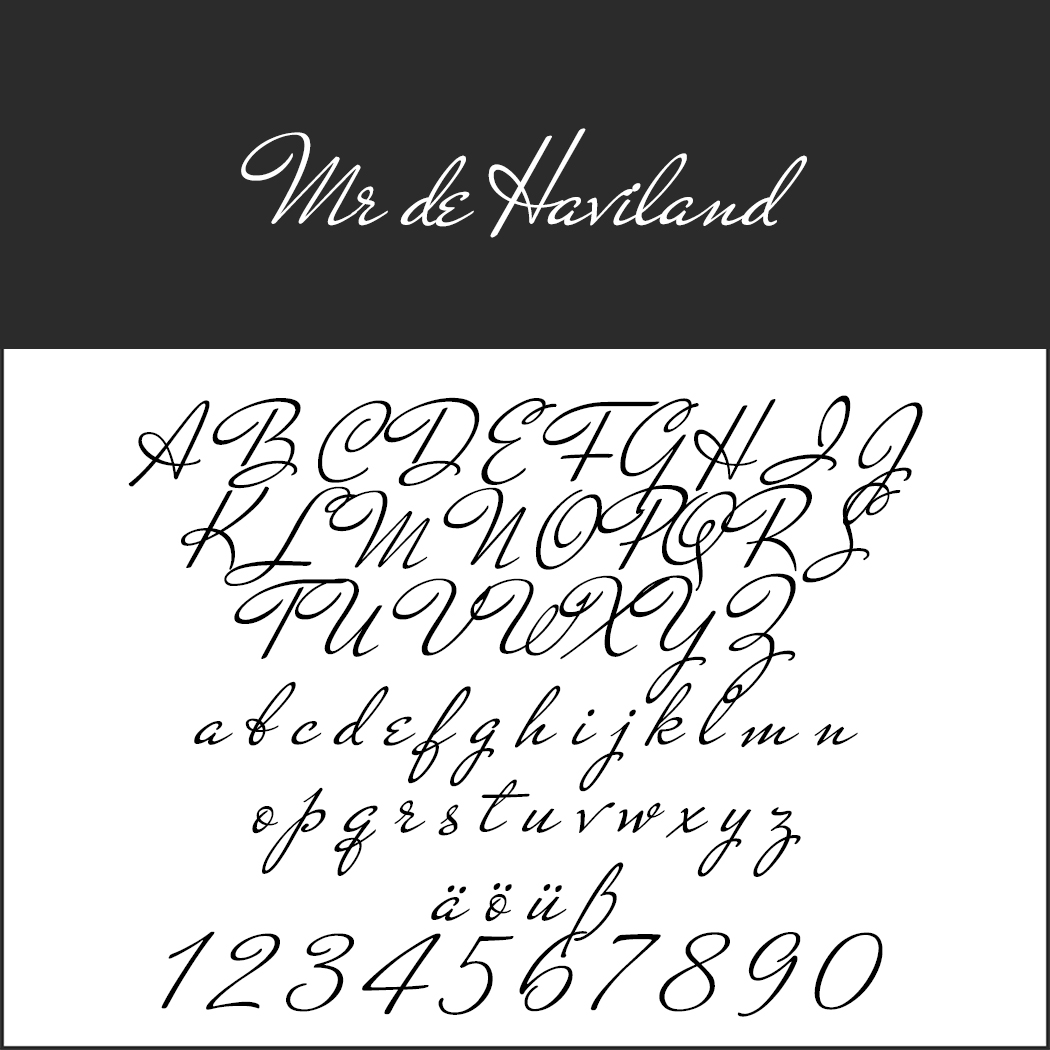
Gli affascinanti font antichi sono in grado di destare nel lettore delle sensazioni che possono essere sfruttate nell’ambito della comunicazione e del marketing. Un viaggio nel tempo attraverso il mondo dei font.
Quando un font si allontana troppo dal tipo di scrittura a cui è più abituato il lettore, salta subito all’occhio. Una capacità che rappresenta già di per sé un valore intrinseco. Tuttavia, la parte più interessante di questo processo consiste proprio nell’analizzare ciò che accade nella mente di chi legge. Infatti, disponendo di un archivio quasi illimitato di immagini, il cervello di una persona adulta è in grado di stabilire immediatamente un’associazione con il passato quando si trova di fronte ai font antichi.
La scrittura gotica rimanda subito a epoche lontane ed è pertanto ideale per pubblicizzare un mercato medievale, il corsivo dall’aspetto nostalgico ricorda più le romantiche lettere d’amore di una volta, mentre i caratteri nello stile Art déco riportano in vita i ruggenti anni ‘20. Prima di optare per un determinato font è consigliabile sottoporlo a individui diversi in modo da prevenire eventuali associazioni indesiderate, poiché l’archivio cerebrale di ogni persona è differente.
Font dallo stile antico
Gli antichi greci e romani incidevano i loro testi nella pietra o li dipingevano su pergamena, delle tecniche che al giorno d’oggi non vengono considerate affatto pratiche: esistono però dei font che riecheggiano proprio lo stile antico di quelle epoche.
Font stilizzato intitolato Art Greco, che ricorda i vecchi font. Visualizzato sia in lettere maiuscole che minuscole, ogni carattere vanta un design geometrico e angolare su uno sfondo bicolore.Art Greco
Nonostante le lettere non corrispondano esattamente agli antichi caratteri (o alla scrittura neogreca), utilizzando questo accattivante font viene subito richiamato il legame con la Grecia. Viene impiegato principalmente in campo gastronomico, tuttavia è adatto anche per altri testi che hanno a che vedere con la civiltà ellenica.
Un grafico che mostra lo stile Roman Font VII, un esempio squisito di vecchi font. Mostra l'alfabeto inglese maiuscolo completo, dalla A alla Z, e numeri romani dalla I alla X in due righe, con un design serif classico.Roman Font 7
Questo font ispirato ai caratteri romani sembra davvero scolpito nella pietra. Sono disponibili solo le lettere maiuscole, mentre per scrivere i numeri è necessario ricorrere a quelli romani.
Font medievali e rinascimentali
Con la diffusione del Cristianesimo l’influenza romana si ridusse sempre di più, un processo che si riflesse anche nella scrittura: le lettere si distanziarono dallo stile romano e diventarono più rotonde. La continua evoluzione delle grafie sfociò nella comparsa dei caratteri gotici e rinascimentali.
Immagine che mostra il font Carolingia senza tempo, un'ode ai vecchi font. Presenta lettere maiuscole dalla A alla Z, lettere minuscole dalla a alla z, caratteri speciali ä, ö, ü, ß e numeri da 0 a 9 su uno sfondo classico in bianco e nero.Carolingia
A partire dalla fine del VIII secolo, durante il regno dei Carolingi, nei monasteri venne ideata una nuova grafia: la minuscola carolina, a cui William Boyd si è ispirato per creare il font Carolingia.
• Design: William Boyd
Viene mostrato un esempio di font gotico intitolato Ute Schwabacher, che presenta lettere maiuscole, minuscole, caratteri speciali (ä, ö, ü, ß) e numeri da 0 a 9 in uno stile ornato tipico dei vecchi font d'epoca.Alte Schwabacher
Dal XII secolo le lettere divennero più squadrate e il flusso di scrittura “spezzato”. È proprio da questa particolare caratteristica che prese vita il concetto tedesco di “Gebrochene Schriften” (letteralmente “grafie spezzate”) utilizzato per indicare la scrittura gotica (vedi anche “Pura nostalgia: font gotici da scaricare gratuitamente”). L’esempio più noto è l’Alte Schwabacher, nato nel XV secolo.
Elegante font in stile corsivo che ricorda i vecchi font, con lettere maiuscole (A-Z) e minuscole (a-z con ä, ö, ü aggiuntive), oltre a numeri (0-9). L'intestazione riporta la scritta Mr de Haviland in uno stile corsivo simile.Mr De Haviland
Uno stravagante font nato negli Stati Uniti durante gli anni ‘30. Non essendo ben leggibile è sconsigliato per testi troppo lunghi, ma è l’ideale per conferire ai propri titoli un aspetto davvero accattivante.